Długie lato
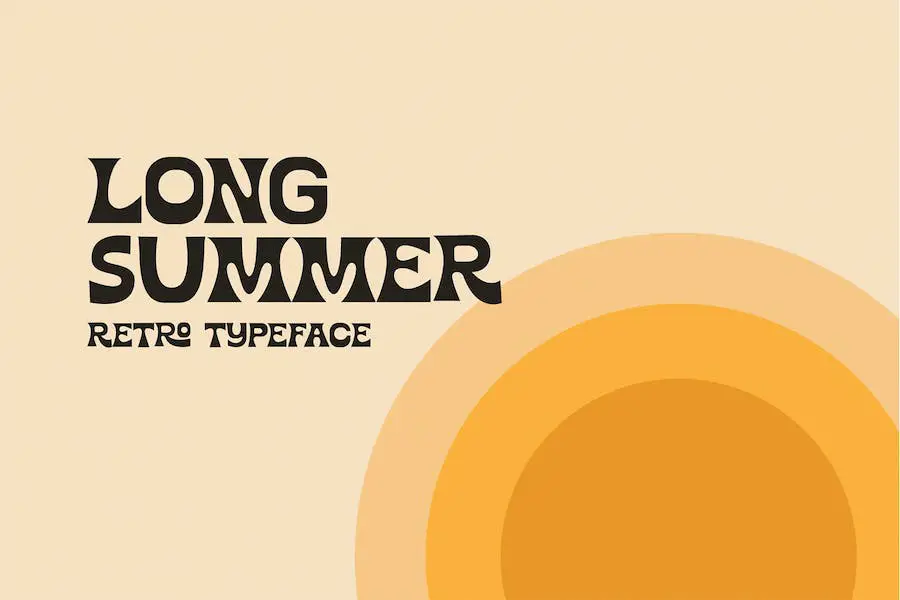
Long Summer – świetna czcionka inspirowana dziećmi kwiatów i surferami z lat 60. i 70. Ta efektowna czcionka doda nostalgicznego i żywego akcentu Twoim projektom.
Funkcjonalny Mrok
Funky Gloom to fantazyjna i nowoczesna czcionka w stylu czarnych liter, idealna do dodania odważnego akcentu Twoim projektom. Niezależnie od tego, czy pracujesz nad tekstem wyświetlanym, czy tekstem głównym, ta czcionka zainspiruje Cię do stworzenia czegoś wyjątkowego i nowoczesnego.
Dzięki alternatywnym znakom możesz z łatwością tworzyć specjalne i wzruszające projekty typograficzne. Idealnie nadaje się do nagłówków, ulotek, kart okolicznościowych, opakowań produktów, okładek książek, drukowanych cytatów, logotypów, projektów odzieży, a nawet okładek albumów.
Czcionka zawiera również znaki interpunkcyjne i ligatury, dzięki czemu jest jeszcze bardziej wszechstronna. Ponadto obsługuje wiele języków, dzięki czemu nadaje się do szerokiej gamy projektów. Nadaj swoim projektom funky i ponury klimat dzięki czcionce Funky Gloom.
Witaj Omen
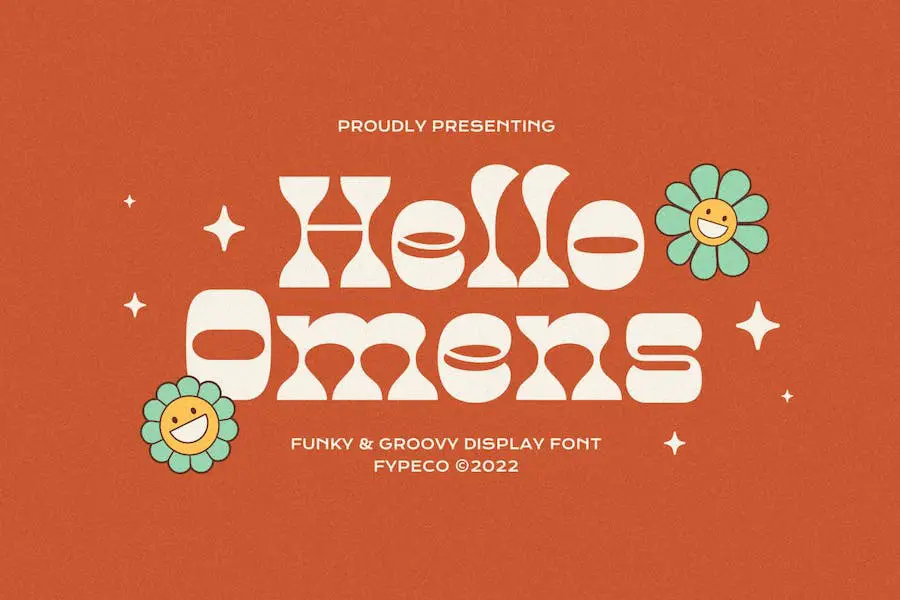
Hello Omens to wyjątkowa czcionka, która wnosi do Twoich projektów fantastyczny klimat retro. Dzięki stylowi liter nawiązującemu do wczesnych lat 70. XX wieku i kapryśnej ery postpsychedelicznej grafiki, ta czcionka idealnie nadaje się do dodania odrobiny nostalgii do Twoich projektów.
Niezależnie od tego, czy pracujesz nad nagłówkiem, cytatem czy układem magazynu, Hello Omens doda Ci dawki osobowości i stylu. Szczególnie dobrze nadaje się do projektów z lat 70.